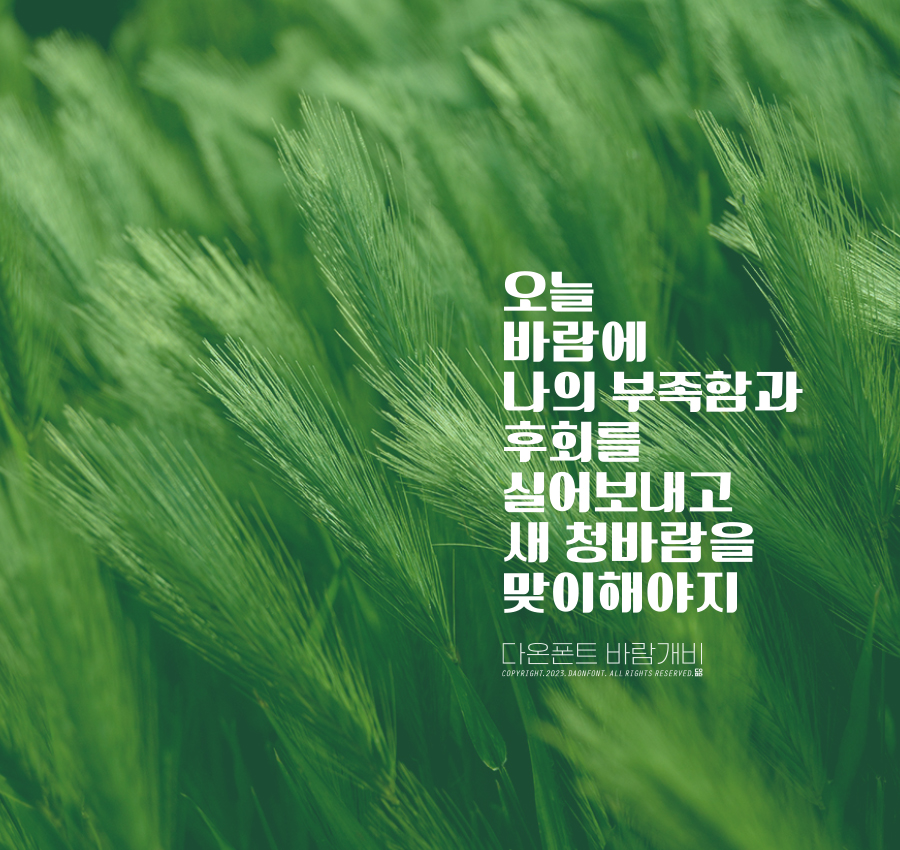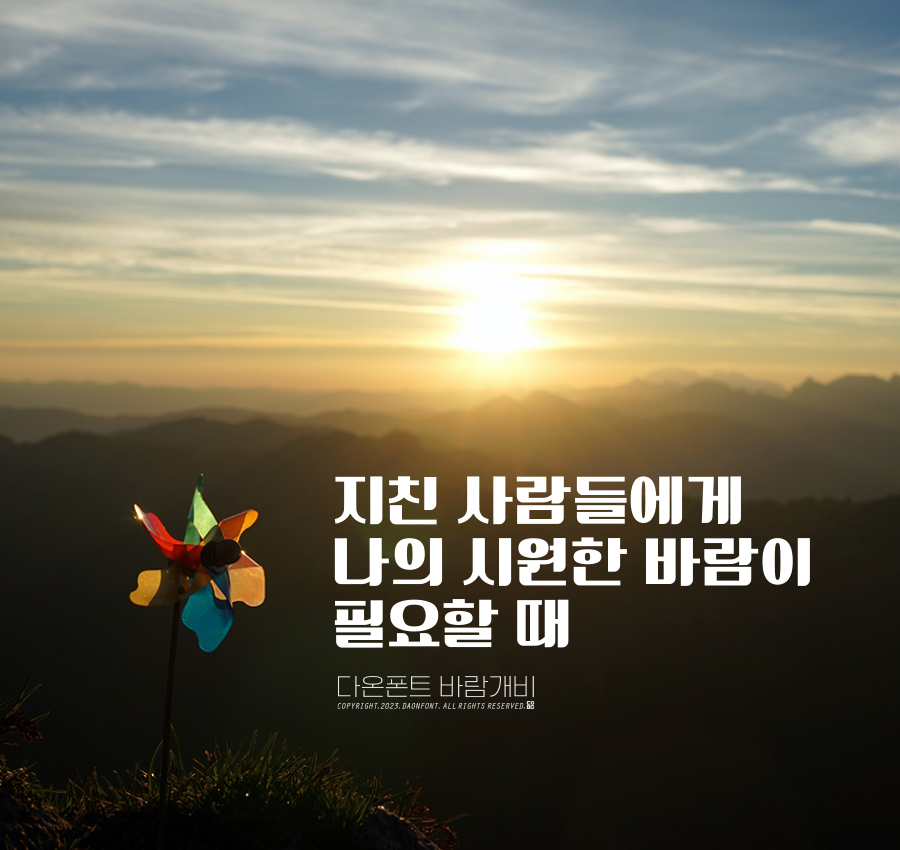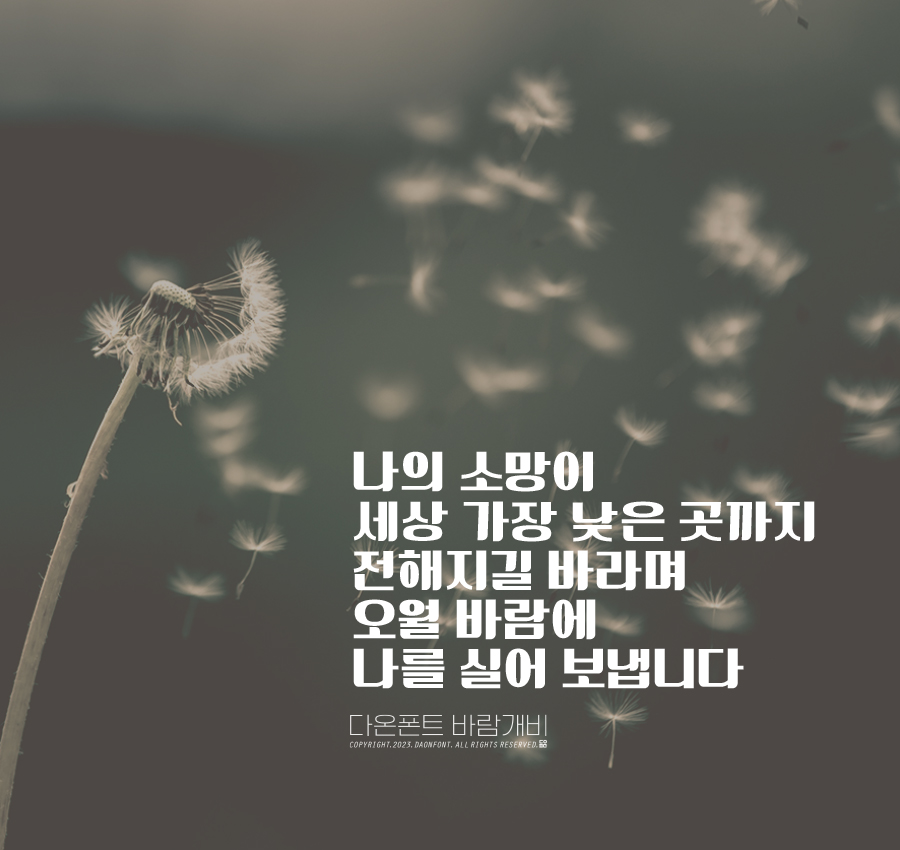
다온폰트 5월 신서체 바람개비 출시 예정
5월 신서체 다온폰트 바람개비가 다음주 화요일에 출시될 예정입니다.
다온폰트 바람개비는 타이틀 서체로 제작되었으며,
시원시원 획을 가진 고딕서체입니다.
이번에 출시되는 다온폰트 바람개비가 여러분들에게 희망의 바람을 가져다주길 바랍니다.